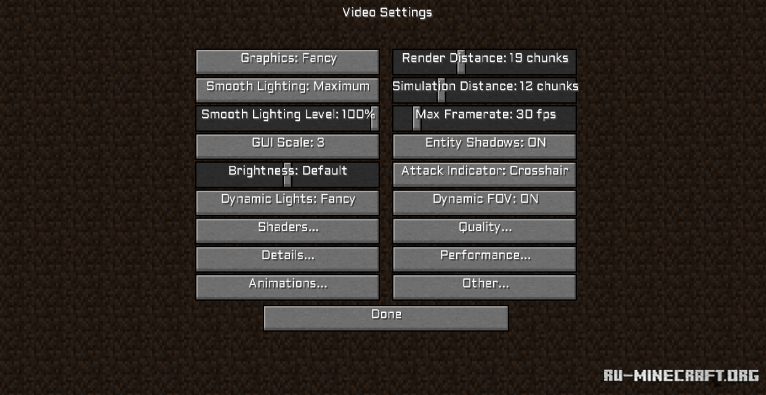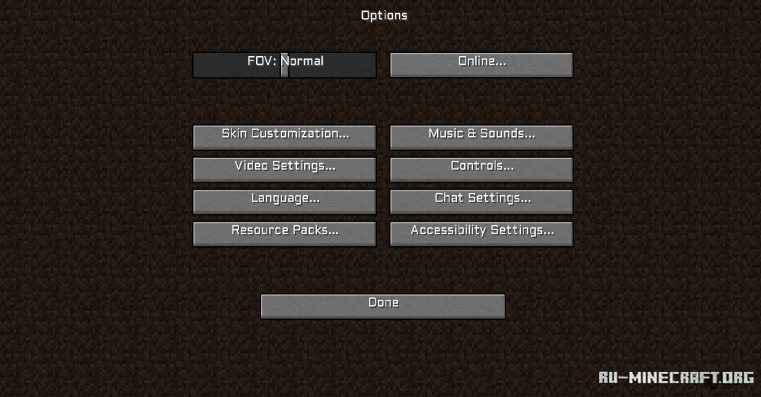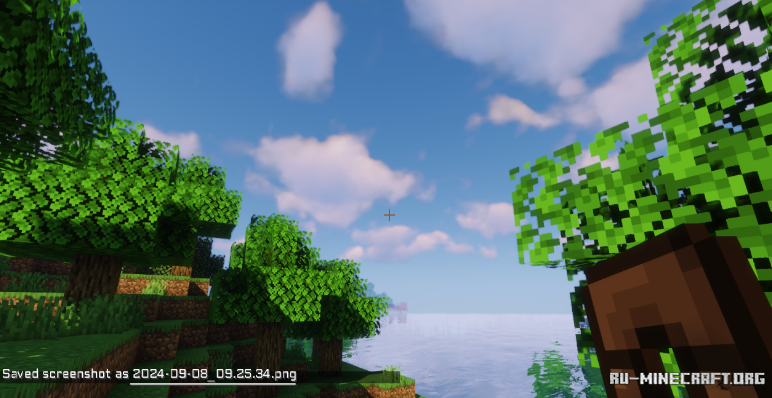
Качественный пакет текстур Tech RPG Font, который в свою очередь позволит вам открыть замечательный вариант изменения привычного шрифта в очень красивом стиле. Если вы любите подобный вариант подобного стиля в собственной игре. Если вы любите такие визуальные обновления с шрифтами, то смело скачивайте !